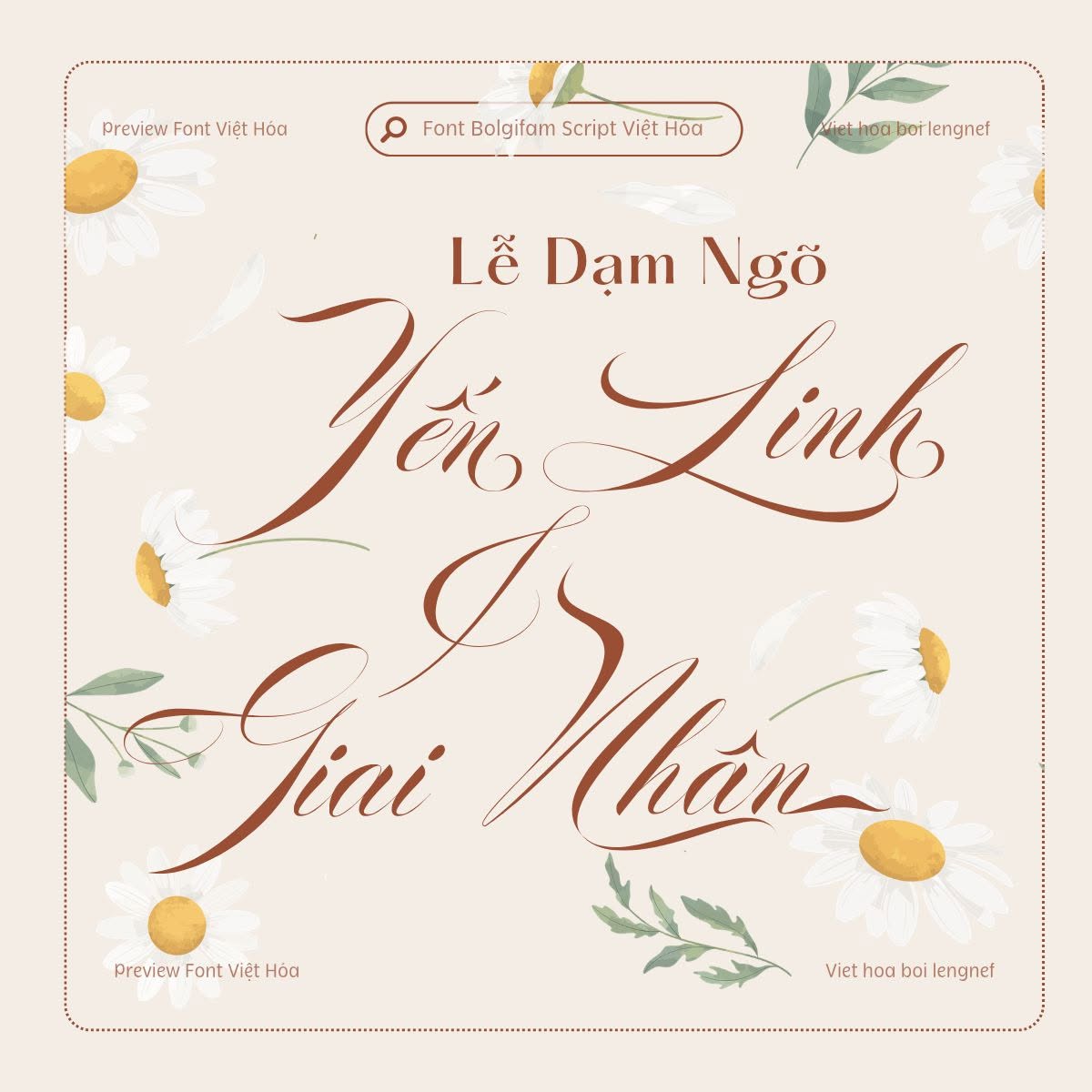
Share Font 79 || LF Bolgifam Script
- Tác giả: Alcode
- Việt hóa: lengnef
Bolgifam Script nằm trong bộ font Bolgifam sang trọng và thanh lịch. Là kiểu font script cổ điển với nhiều ký tự nối và ký tự đặc biệt có thể dùng trong mọi dự án thiết kế và kết hợp hoàn hảo với bất kỳ font nào khác.
Với phong cách vừa thanh lịch, cổ điển mà sang trong này nó rất phù hợp với các thiết kế như thiệp cưới, bìa sách, thiệp chúc mừng, logo, thương hiệu, danh thiếp và chứng chỉ.